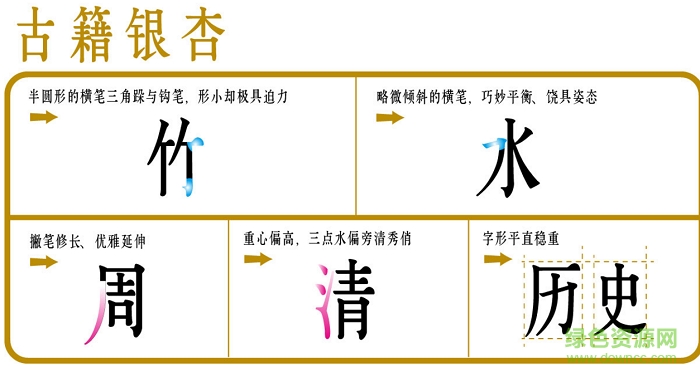
華康古籍銀杏w3 p字體是一款極具古韻的華康字體,這款字體的筆畫細(xì)膩,外形優(yōu)雅,構(gòu)形精美,藝術(shù)感十足,使用效果令人驚艷,喜歡華康古籍銀杏體的小伙伴快來下載吧!
以《天工開物》為底本所開發(fā)的古籍銀杏,傳承自明代科學(xué)家宋應(yīng)星(1587~1663)《天工開物》書中的版刻風(fēng)格,間距挑高拉長如千年銀杏林,橫筆半圓形的筆劃則細(xì)膩優(yōu)雅如銀杏葉,閱讀起來好似仰望銀杏古老參天的風(fēng)華,極具視覺美感。適合內(nèi)文書寫,通篇文章以直書排版,更增添古籍版刻印刷的風(fēng)貌。
古籍銀杏字體重心高且平直穩(wěn)定,橫筆末端成半圓弧形,如銀杏葉般;撇捺間延伸從容自在,清秀雅致。
古籍書體系列保留了數(shù)百年前工匠們雕刻時所留下的手感,微小不精準(zhǔn)的筆劃曲線,若以數(shù)碼字體的角度來看或許屬于瑕疵,但卻是當(dāng)時工匠技藝的留存;更保留了每套原書印刷排版的閱讀效果,讓古風(fēng)雅韻經(jīng)典再現(xiàn)。